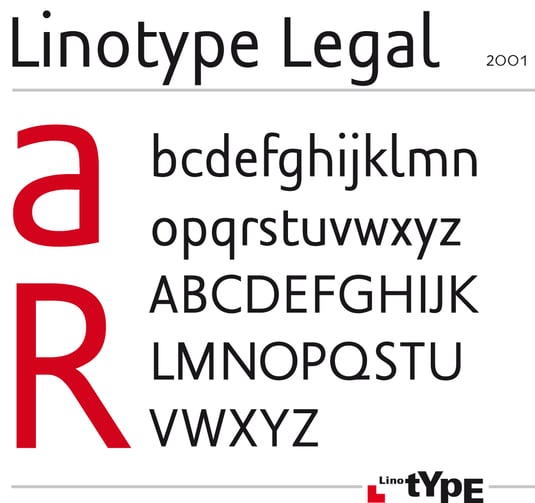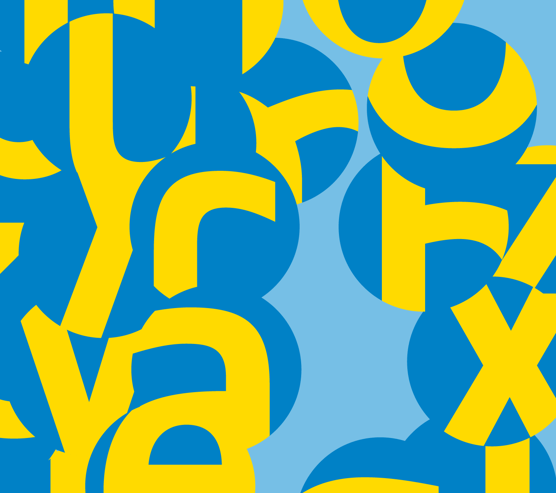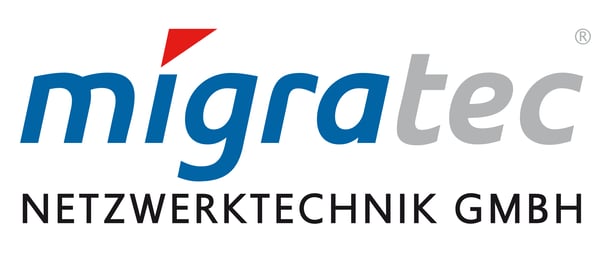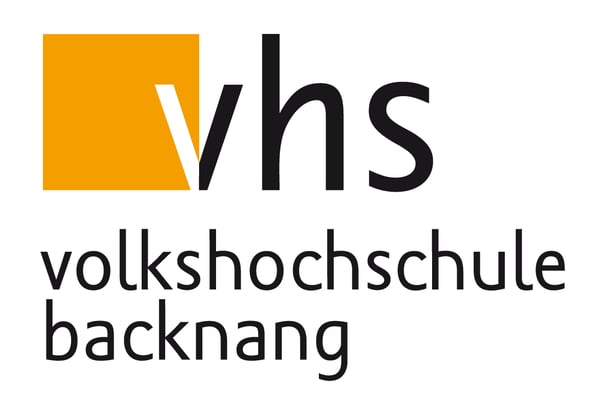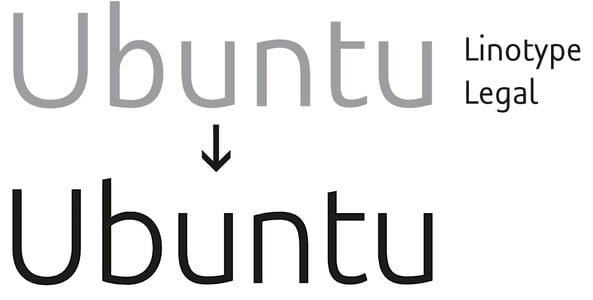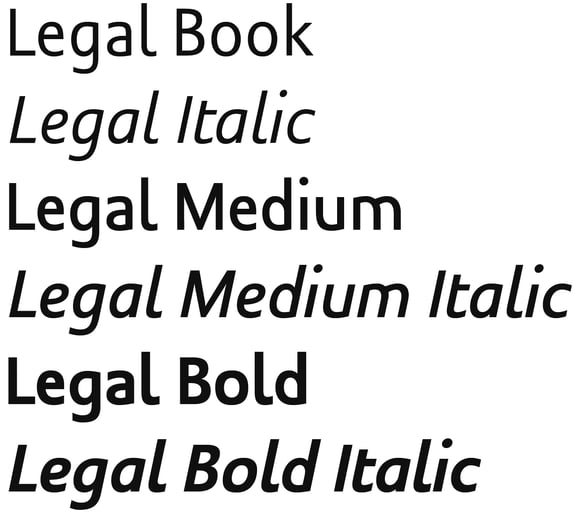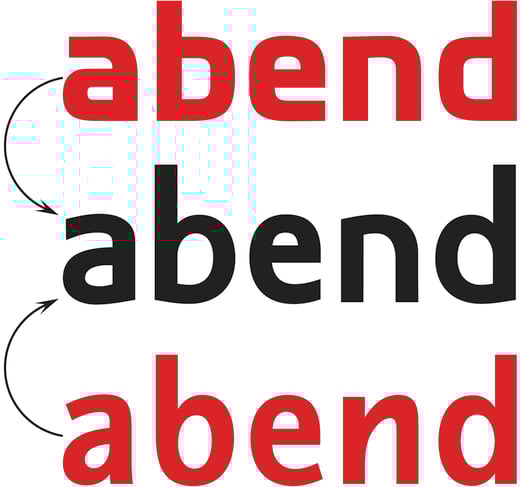
Linotype Legal
Die Schrift »Legal« entstand aus einem Grotesk-Projekt, das eine serifenlose Leseschrift mit gleichmäßiger Strichstärke zum Ziel hatte. Durch Überblenden (morphen) von verschiedenen Entwürfen kam ich zu einer sehr reduzierten, dabei aber klaren Schrift. Einzelne Buchstaben wurden stark vereinfacht und mit Formelementen einer Schrift aus den 70er Jahren vermischt. Beim Lesen fällt dies kaum auf, während bei großen Buchstaben eine starke Eigenwilligkeit zum Vorschein kommt.
Zunächst war unter dem Namen minuska eine Schrift ohne Großbuchstaben vorgesehen. Diese bekam später noch einen Satz Großbuchstaben und einen neuen Namen. Ende 2001 wurde die Legal von der Linotype Library lizenziert. Von 2003 bis 2014 diente sie (ohne Versalien) als Logo- und Auszeichnungsschrift für die Volkshochschule Backnang und gab dieser ein sehr eigenständiges, sympathisches Erscheinungsbild mit lokalem Bezug.
Für das Logo des Linux-Betriebssystems Ubuntu wurde die etwas modifizierte Legal verwendet.